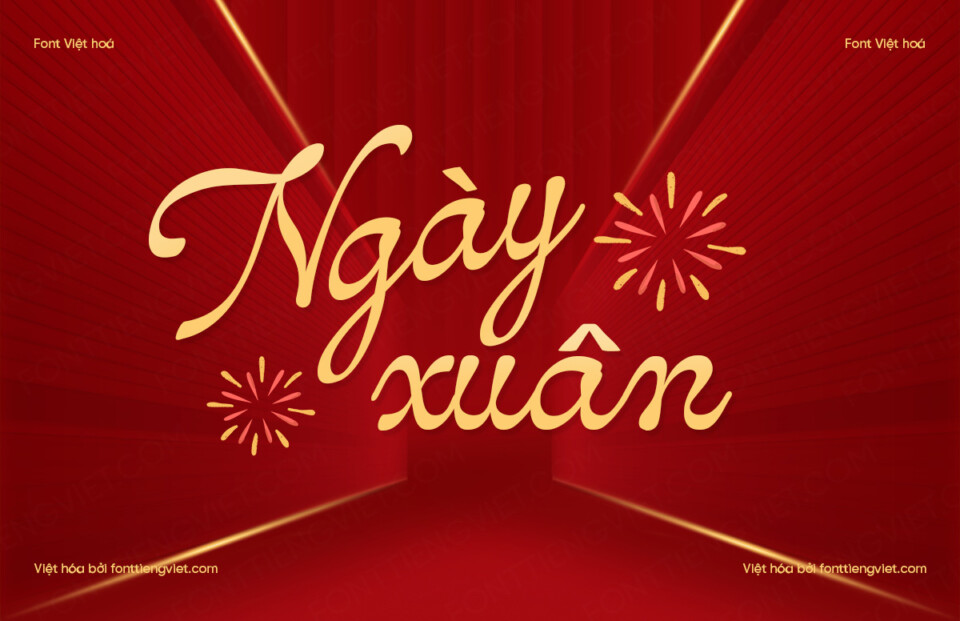
Font việt hoá 1FTV VIP Amhiney – Font tết
Font việt hoá 1FTV VIP Amhiney – Font tết: Lựa chọn đẳng cấp cho thiết kế Xuân 2026
Chào mừng bạn đến với thế giới sáng tạo nơi những con chữ không chỉ để đọc mà còn để cảm nhận vẻ đẹp văn hóa truyền thống. Trong không khí hối hả chuẩn bị cho mùa lễ hội lớn nhất năm, việc tìm kiếm một bộ Font Miễn Phí chất lượng cao là ưu tiên hàng đầu của mọi nhà thiết kế. Font việt hoá 1FTV VIP Amhiney – Font tết nổi lên như một hiện tượng trong cộng đồng đồ họa Việt nhờ sự kết hợp hoàn mỹ giữa nét bút lông mềm mại và cấu trúc hiện đại. Bộ font này không chỉ giải quyết vấn đề hiển thị tiếng Việt có dấu mà còn mang đến cái hồn của sự may mắn, thịnh vượng trong từng nét thanh nét đậm, giúp mọi ấn phẩm trở nên rạng rỡ và thu hút hơn bao giờ hết.
Khám phá đặc điểm nổi bật của Font việt hoá 1FTV VIP Amhiney – Font tết
Điều làm nên sự khác biệt của bộ chữ này chính là tính ứng dụng đa dạng và độ hoàn thiện cực kỳ chi tiết. Đối với các bạn học sinh hay những người mới bắt đầu học thiết kế, việc sở hữu một bộ font đã được xử lý kỹ lưỡng về bảng mã sẽ giúp tiết kiệm tối đa thời gian căn chỉnh.
Nét vẽ nghệ thuật đậm chất Á Đông
Font việt hoá 1FTV VIP Amhiney – Font tết mang trong mình những đường cong uốn lượn lấy cảm hứng từ thư pháp cổ điển nhưng được tinh giản để phù hợp với thẩm mỹ đương đại. Các ký tự được thiết kế với độ dày vừa phải, tạo cảm giác chắc chắn nhưng vẫn giữ được sự thanh thoát cần thiết. Điều này giúp các tiêu đề trên thiệp chúc mừng, banner quảng cáo hay bao bì bánh kẹo Tết trở nên nổi bật, sang trọng mà không gây cảm giác rối mắt cho người xem.
Khả năng tương thích và hỗ trợ tiếng Việt hoàn hảo
Một trong những nỗi lo lớn nhất khi sử dụng font ngoại chính là lỗi font khi gõ dấu tiếng Việt. Tuy nhiên, với phiên bản Font việt hoá 1FTV VIP Amhiney – Font tết, toàn bộ các dấu câu như sắc, huyền, hỏi, ngã, nặng đều được đặt đúng vị trí, đảm bảo tính thẩm mỹ và sự dễ đọc. Bộ mã Unicode chuẩn giúp bạn dễ dàng sử dụng font trên các phần mềm đồ họa chuyên nghiệp như Photoshop, Illustrator hay thậm chí là các ứng dụng văn phòng cơ bản.
Ứng dụng thực tế của Font việt hoá 1FTV VIP Amhiney – Font tết trong đời sống
Sức mạnh của bộ font này nằm ở khả năng biến hóa linh hoạt trong nhiều bối cảnh khác nhau, từ môi trường học đường đến các dự án thương mại cao cấp.
Trang trí bảng tin và thiệp chúc Tết học đường
Tại các trường học, việc trang trí bảng tin hay làm thiệp tặng thầy cô, bạn bè là hoạt động không thể thiếu mỗi dịp xuân về. Sử dụng Font việt hoá 1FTV VIP Amhiney – Font tết giúp các em học sinh dễ dàng tạo ra những sản phẩm thủ công mang nét đẹp truyền thống. Những dòng chữ “Chúc Mừng Năm Mới” hay “Vạn Sự Như Ý” sẽ trở nên trang trọng và đầy ý nghĩa, thể hiện sự chỉn chu và lòng biết ơn của người tặng đối với người nhận.
Thiết kế bộ nhận diện thương hiệu mùa lễ hội
Đối với các doanh nghiệp, việc thay đổi diện mạo sản phẩm theo mùa là chiến lược marketing hiệu quả. Bộ font này cực kỳ phù hợp để làm tiêu đề cho các chiến dịch giảm giá, menu món ăn ngày Tết hoặc các thẻ quà tặng tri ân khách hàng. Sự đồng nhất và tinh tế của bộ chữ giúp nâng tầm giá trị thương hiệu, tạo ấn tượng mạnh mẽ về một doanh nghiệp coi trọng giá trị văn hóa dân tộc.